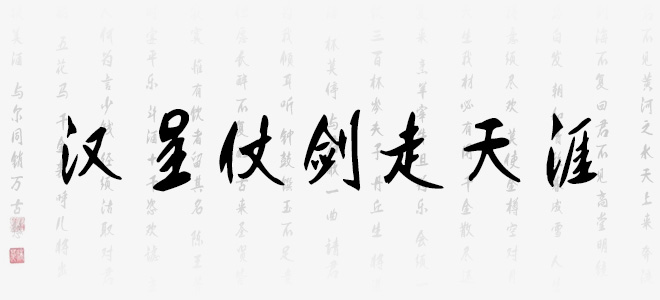
漢呈仗劍走天涯字體是漢呈字庫(kù)新推出的一款個(gè)性手寫(xiě)書(shū)法字體,書(shū)寫(xiě)頗具江湖氣息,非常有意思,適合藝術(shù)設(shè)計(jì)、平面宣傳設(shè)計(jì)、網(wǎng)頁(yè)設(shè)計(jì),書(shū)法字帖等領(lǐng)域,歡迎喜歡漢呈仗劍走天涯字體的朋友前來(lái)下載使用。
漢呈仗劍走天涯字體